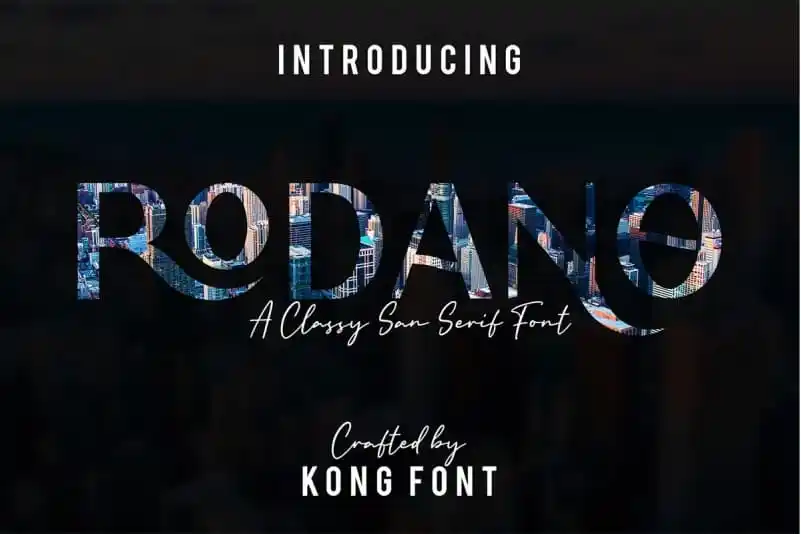
Rodano Display Font – Fonte Grátis
Rodano Display Font
A Rodano Display Font é uma elegante solução para designers que buscam uma fonte moderna com um toque de sofisticação. Desenvolvida pelo site 99designs, essa fonte minimalista e luxuosa proporciona um look atemporal e contemporâneo em trabalhos gráficos variados. Seja para criar marca de produtos exclusivas ou assinaturas elegantes, para conceitos visuais criativos como anúncios casais românticos ou capas de revistas modernizadas, a Rodano oferece um look sofisticado e moderno que combina perfeitamente com qualquer projeto. Seja qual seja o seu objetivo gráfico, é provável que encontre uma solução perfeita neste belo recurso do mundo da tipografia.